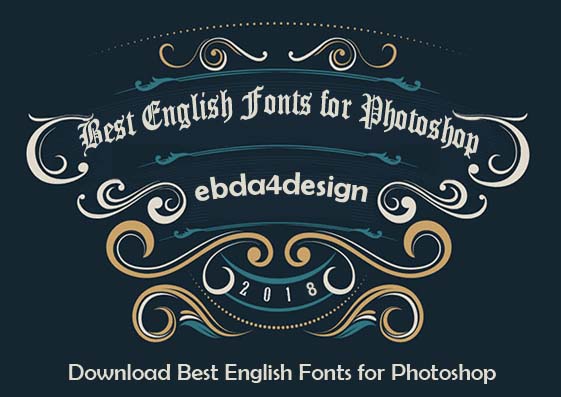
تحميل خطوط إنجليزية مجاناً للتصميم الاحترافي 𝓔𝓷𝓰𝓵𝓲𝓼𝓱 𝓕𝓸𝓷𝓽𝓼
تحميل أروع خطوط إنجليزية مجاناً للفوتوشوب وللتصميم الاحترافي
هذا القسم هو عباره عن مكتبة لتحميل أرقى وأروع خطوط التصميم الانجليزي الاحترافية
نبذه مختصره عن تاريخ ونشأة اللغة الإنجليزية القديمة
اللغة الإنجليزية اُستخدمت في الكتابة لاول مرة في الأحرف الأنجلوسكسونية الرونية و كان هذا في القرن الخامس قبل الميلاد. هذه الحروف الأبجدية وصلت إلى ما هي عليه الآن كما نراها في انجلترا ، جنبا إلى جنب مع الشكل الأولى من اللغة نفسها، من قبل المستوطنين الأنجلو سكسونيين . نجا القليل من هذا الشكل من اللغة الإنجليزية القديمة المكتوبة ، وهي في معظمها رموز أو نقوش
أو بقايا حروف للغه الأبجدية اللاتينية، التي قدمها المبشرون المسيحيون، وقد بدأت اللغه الإنجليزيه أن تحل محل شكل الأحرف الأنجلوسكسونية الرونية منذ حوالى القرن السابع الميلادي ، على الرغم من أن اللغتين بقيتا مستعملتين معا لبعض الوقت. وقد اشتقت وتطورت اللغه الإنجليزيه منذ ذلك الحين من عدة لغات حيه قديمه مثل اللغة اللاتينيه واللغه الآيرلنديه القديمه
في عام 1011، استخدم كاتب يدعى بيرتوفو الأبجدية الإنجليزية القديمة بغرض الترقيم . أولا سرد حروف الأبجدية اللاتينية ال24 (بما في ذلك العطف) في البداية ، وهي الحروف التاليه
A B C D E F G H I K L M N O P Q R S T V X Y Z & ⁊ Ƿ Þ Ð Æ
وبذلك نشأت لغه إنجليزيه مستقله بحد ذاتها عن اللغتين اللاتينه والآيرلنديه التي اشتقت أساساً منهما
خط رمضان Ramadan Font
خط Floraison des Amours
خط Caviar Dreams Font
خط الأكشن والرعب Another Danger Font
خط شهادات التقدير Certificate Font
خط Geo Sans Font
خط Old English Text MT Font
خط Palace Script MT Semi Font
خط قناة روتانا Rotana Channel Font
خط لافندر Lavender Font